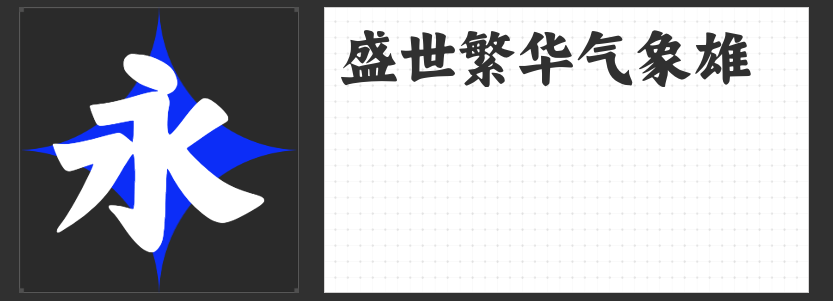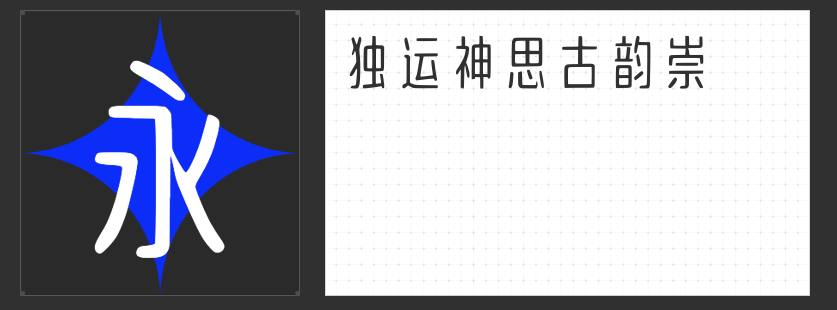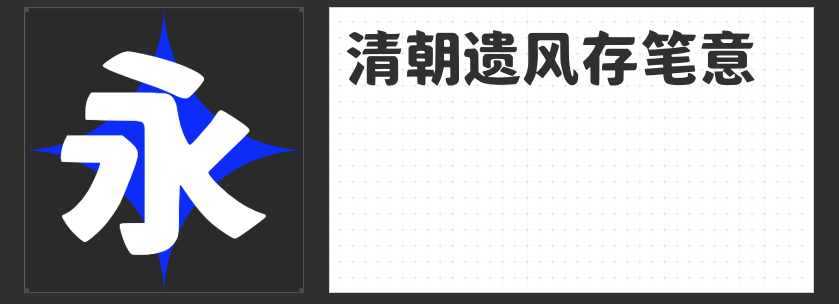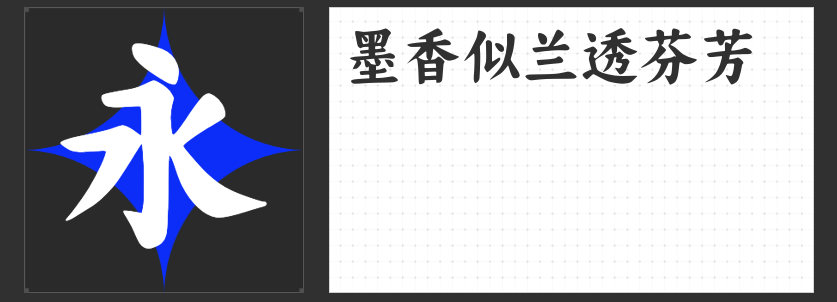
“小欣大萌”系列字体:穿越古今的视觉盛宴
在数字化的今天,字体不仅仅是文字的载体,更是文化与艺术的融合体。今天,要为大家推荐的是“小欣大萌”系列字体,这一系列的四款字体,它们各具特色,仿佛让我们穿越时空,与古人的智慧与美学相遇。
首先,让我们了解“大萌秦”。这款字体以秦朝的小篆为基础,巧妙地融入了现代字型的元素。小篆的古典韵味与现代阅读习惯相结合,使得“大萌秦”字体既保持了传统书法的精髓,又易于现代人阅读和理解。每一个字都仿佛带着历史的厚重,让人在书写和阅读中感受到那份沉淀千年的文化底蕴。
接下来是“大萌清”,这款字体以清朝民国时期的风格为蓝本,仿佛让我们置身于那个宣纸轻展、墨香四溢的年代。其字体风格与民国风韵交织,构成了一幅跨越时空的画卷,让人在欣赏字体之美的同时,也能感受到那个时代的气息与韵味。
“大萌宋”则是一款温润仿宋字体,它不仅承载着历史的厚重,更在现代设计的舞台上绽放异彩。其独特的温润质感,让人仿佛能穿越时空,与古人的风雅对话。这款字体将古人的智慧与现代审美巧妙融合,展现出一种跨越时空的美学魅力。
最后,让我们来看看“大萌唐”。这款微胖楷体以盛唐气象为灵感,字体圆润饱满,笔触间流露出大唐盛世的繁荣与自信。每一个字都仿佛带着那个时代的辉煌与魅力,让人在字里行间感受到那份跨越千年的骄傲与荣耀。
“小欣大萌”系列字体,每一款都蕴含着丰富的文化内涵和独特的美学价值。它们不仅是我们日常书写和阅读的得力助手,更是我们与古人智慧与美学相遇的桥梁。快来选择一款你喜欢的“小欣大萌”系列字体,开启你的穿越古今的视觉盛宴吧!